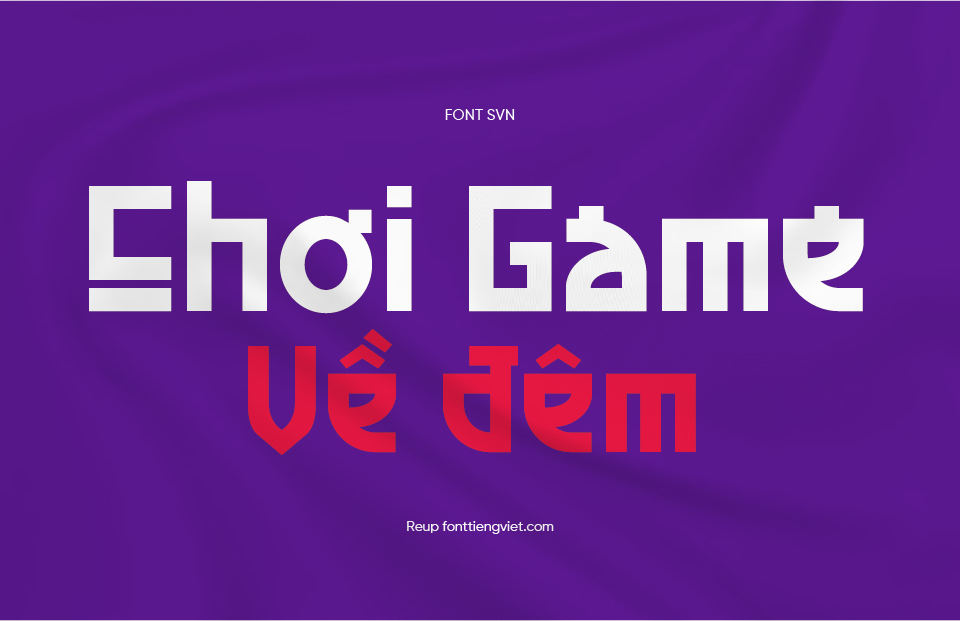
Font việt hóa SVN Money Game
Giới thiệu về Font việt hóa SVN Money Game
Trong thế giới đồ họa hiện đại, việc lựa chọn một Font Miễn Phí chất lượng là yếu tố then chốt để tạo nên sự khác biệt. Font việt hóa SVN Money Game là một bộ font chữ độc đáo, mang phong cách hiện đại và đầy cá tính. Được thiết kế với những đường nét mạnh mẽ, dứt khoát, bộ font này đặc biệt phù hợp cho các dự án thiết kế liên quan đến trò chơi, thương hiệu thể thao hoặc các ấn phẩm quảng cáo cần sự đột phá. Việc sử dụng font chữ đã được việt hóa giúp các nhà thiết kế tại Việt Nam dễ dàng trình bày nội dung tiếng Việt mà không lo lỗi font hay thiếu dấu.
Đặc điểm nổi bật của Font việt hóa SVN Money Game
Phong cách thiết kế sáng tạo
Bộ Font việt hóa SVN Money Game sở hữu cấu trúc hình khối vững chãi nhưng không kém phần linh hoạt. Các ký tự được tinh chỉnh tỉ mỉ để tạo ra sự cân đối trên mọi bề mặt hiển thị. Đây là lựa chọn tuyệt vời cho các tiêu đề lớn, banner website hoặc ảnh bìa mạng xã hội. Sự kết hợp giữa nét dày và các góc cạnh tinh tế giúp thông điệp của bạn trở nên nổi bật và thu hút thị giác ngay từ cái nhìn đầu tiên.
Tính ứng dụng thực tế cao
Không chỉ dùng cho game, font chữ này còn xuất hiện phổ biến trong thiết kế áo thun, poster sự kiện và bao bì sản phẩm. Nhờ khả năng hiển thị rõ nét, nó hỗ trợ tốt cho cả in ấn lẫn hiển thị kỹ thuật số. Cộng đồng thiết kế đánh giá cao bộ font này bởi sự ổn định và phong cách chuyên nghiệp mà nó mang lại cho tác phẩm phẩm tổng thể.